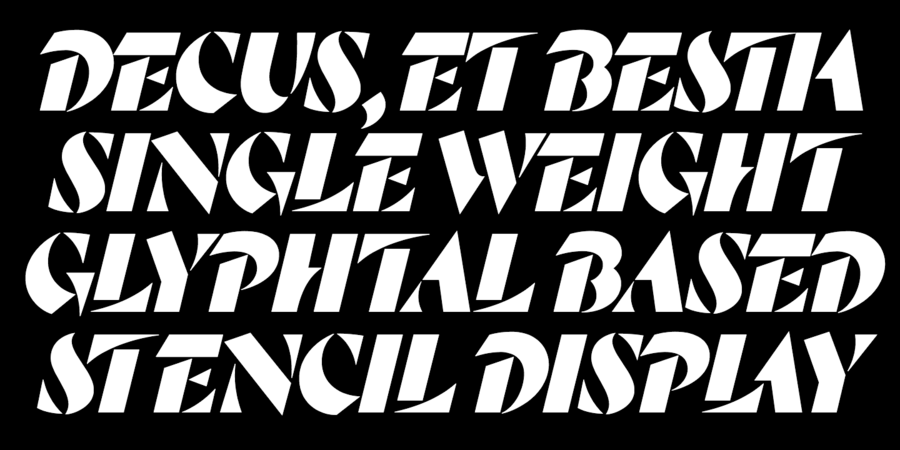
Rozza – це трафаретний курсивний наджирний шрифт для екстремальної акциденції. Дивлячись на ці літери легко згадати історію про красуню та чудовисько, що цілком зрозуміло. З одного боку шрифт страшний і небезпечний, а з іншого – в ньому пульсує краса і пристрасть. Спробуйте поєднати Rozza з Displace, вийде прекрасна шрифтовая пара. Шрифт розробив Денис Серебряков у 2017 році.
Асоціації з сімейством шрифтів RozzaОсобистість і характер гарнітури:
важкий, сміливий, характерний, оригінальний, помітний, дивний, гучний, гострий, монументальний, динамічний, артистичний, виразний, яскравий, ексцентричний, химерний, різкий, чіткий, нічний, холодний, архітектурний, твердий, чорний, живий, ритмічний, грайливий, швидкий, стрімкий, сильний, дикий, активний, експресивний, вишуканий, багатий, салонний, урочистий, дзвінкий, благородний, точний, майстерний, художній, красивий, прекрасний, блискучий, розкішний, дорогий, елітний, якісний, знаменитий, ефектний, модний, переконливий, амбітний, глянцевий, рівний, гордий, театральний, драматичний, пристрасний, сексуальний, гламурний, культурний, добірний, сучасний, міський, впевнений, святковий, претензійний, романтичний, привабливий, екстравагантний, вільний, вольний, колючий, естетський, нонконформістський, експериментальний
кіно, анімація, театр, архітектура, скульптура, головокрутка, нічний клуб, косметика, мода, опера, музика, розкіш, вино, ресторан, преміум, прикраса, перукарня, дизайн, карти, драма, шоколад, кафе, взуття, кава, фарба, алкоголь, цукерки, розваги, бар, парфумерія, парфуми, інтер'єр, люкс, краса, одяг, бутік, ювелір, Модель, салон, туфлі, каблук, романтика, кохання, сукня, нагорода, Трофей, графіка, ілюстрація, вечір Гарнітура має ознаки стилів: